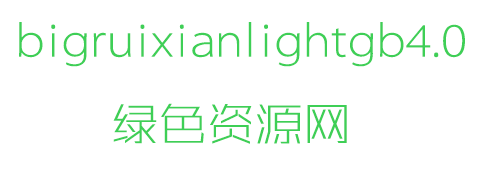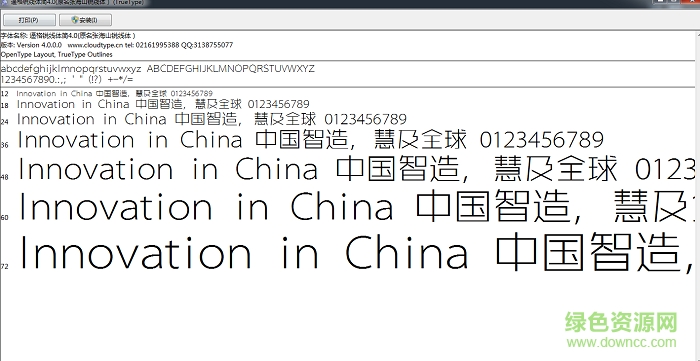
bigruixianlightgb4.0 字體
bigruixianlightgb4.0字體又叫逼格銳線體簡4.0,是一款線條銳利,筆畫纖細(xì)的個性字體,用于廣告字體或包裝設(shè)計(jì)方面都可以,綠色資源網(wǎng)還有超多商業(yè)字體藝術(shù)字體供字體愛好者選擇,需要的朋友快來下載吧!
bigruixianlightgb4.0 字體